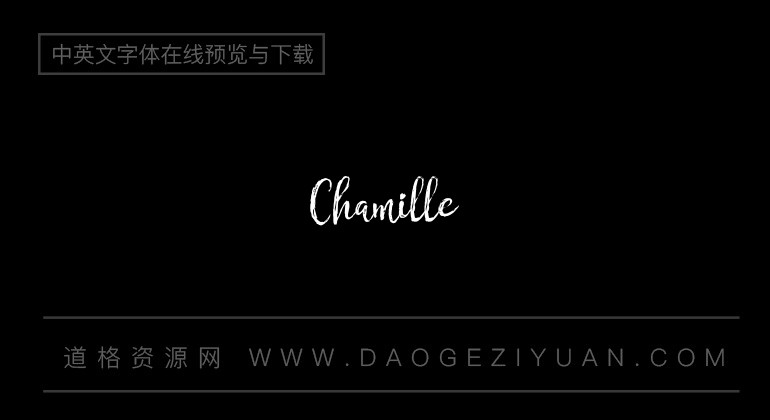
Chamille
Chamille 是一款英文字体,由英国设计师Matthew Carter设计。它是一款精致而优雅的字体,让文字充满生机,具有优雅的外观和独特的风格。它的特点是文字清晰可辨,字体的笔画细腻,给人以温柔的感觉,可以用于报纸、杂志、书籍、海报等印刷品的设计。
Chamille是一款非常不错的手写艺术字体,具有很好的视觉感,适合于文化类的宣传设计、商业类品牌的广告和产品包装设计以及个性化文字排版等较多场景。